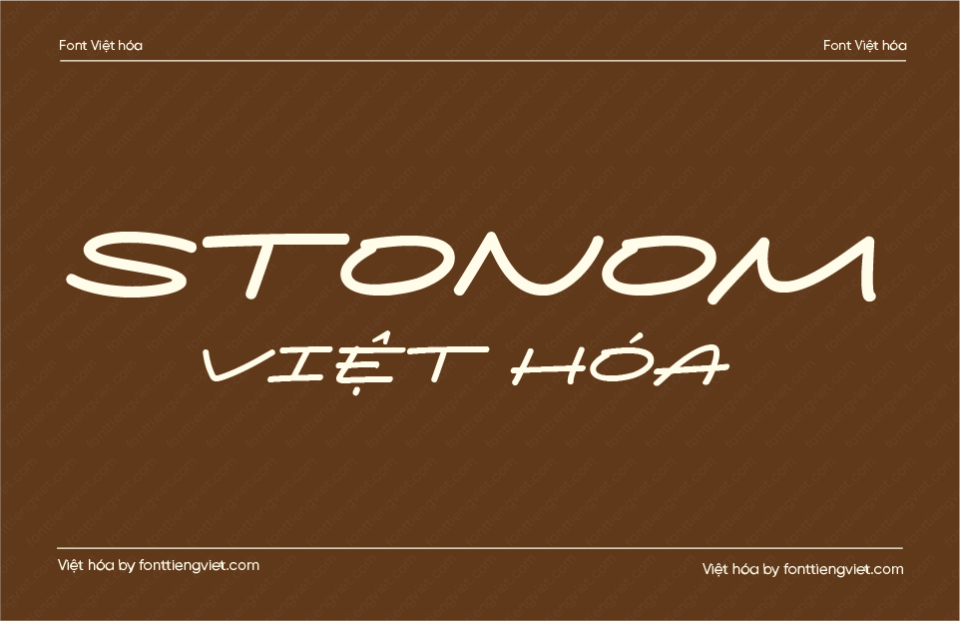
Giới thiệu về bộ Font Việt hóa 1FTV Stonom
Trong thế giới thiết kế đồ họa hiện đại, việc tìm kiếm một bộ Font Chữ vừa mang tính thẩm mỹ cao vừa hỗ trợ đầy đủ tiếng Việt là điều vô cùng quan trọng. Font Việt hóa 1FTV Stonom nổi lên như một lựa chọn hàng đầu nhờ phong cách tối giản nhưng không kém phần tinh tế. Đây là bộ font được tinh chỉnh kỹ lưỡng về dấu câu, giúp các bạn học sinh và thầy cô giáo dễ dàng ứng dụng vào việc làm bài thuyết trình, thiết kế báo tường hay các tài liệu học tập sinh động.
Đặc điểm nổi bật của 1FTV Stonom
Bộ font này sở hữu những đường nét thanh thoát, hiện đại và cực kỳ dễ đọc ngay cả ở kích thước nhỏ. Font Việt hóa 1FTV Stonom không chỉ phù hợp cho các tiêu đề lớn gây ấn tượng mà còn hoạt động tốt trong các đoạn văn bản dài. Sự cân bằng giữa các khoảng cách chữ giúp người xem không bị mỏi mắt, tạo nên sự chuyên nghiệp cho mọi bản thiết kế học đường.
Cách ứng dụng Font Việt hóa 1FTV Stonom trong học tập
Các bạn có thể sử dụng bộ font này để làm mới các slide PowerPoint, giúp bài giảng của thầy cô trở nên lôi cuốn hơn. Ngoài ra, việc kết hợp 1FTV Stonom với các gam màu sáng sẽ tạo nên những sản phẩm truyền thông trường học bắt mắt. Hãy thử nghiệm ngay để thấy sự khác biệt mà bộ font này mang lại cho không gian sáng tạo của bạn.
Kết luận về bộ font 1FTV Stonom